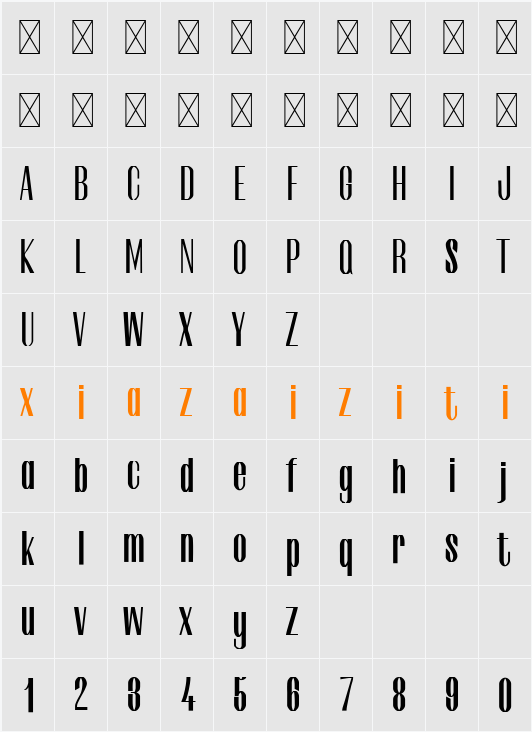
Zayani Demo
Zayani Demo,这款字体结构工整、笔画清晰,兼顾美观与易读性,适用于标题、正文、海报、包装、LOGO 等多种场景。字形优雅稳定,风格百搭耐看,适配日常排版与创意设计,让文字呈现更舒适、更具质感。Zayani Demo一笔一画,皆是细节,以均衡的比例、流畅的线条打造舒适视觉体验,字形端正大气,风格简约现代。无论是商业设计、品牌宣传还是日常排版,都能轻松驾驭,让文字更有格调与力量。Zayani Demo字体下载。
• 设计师: Faraz Ahmad